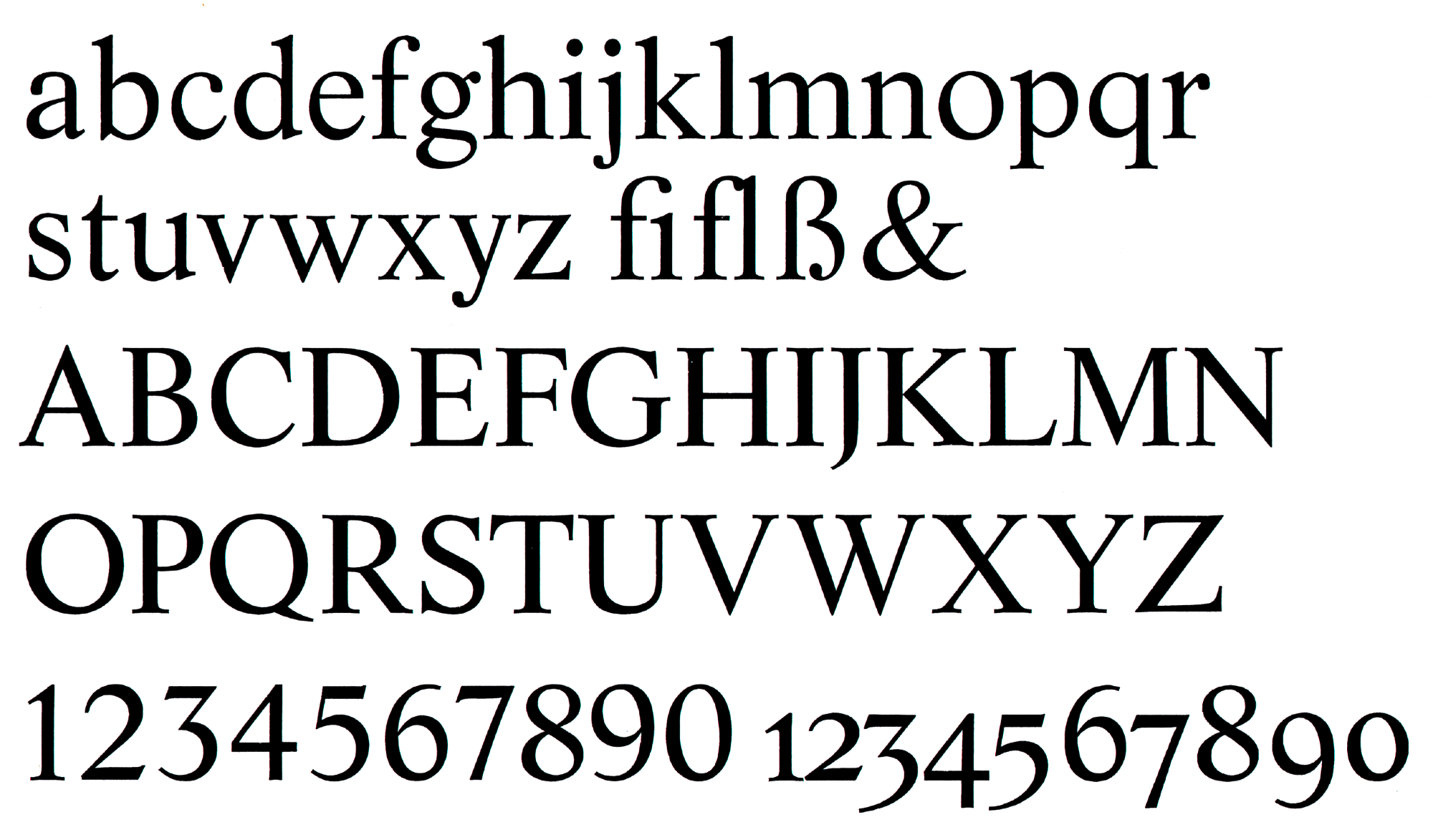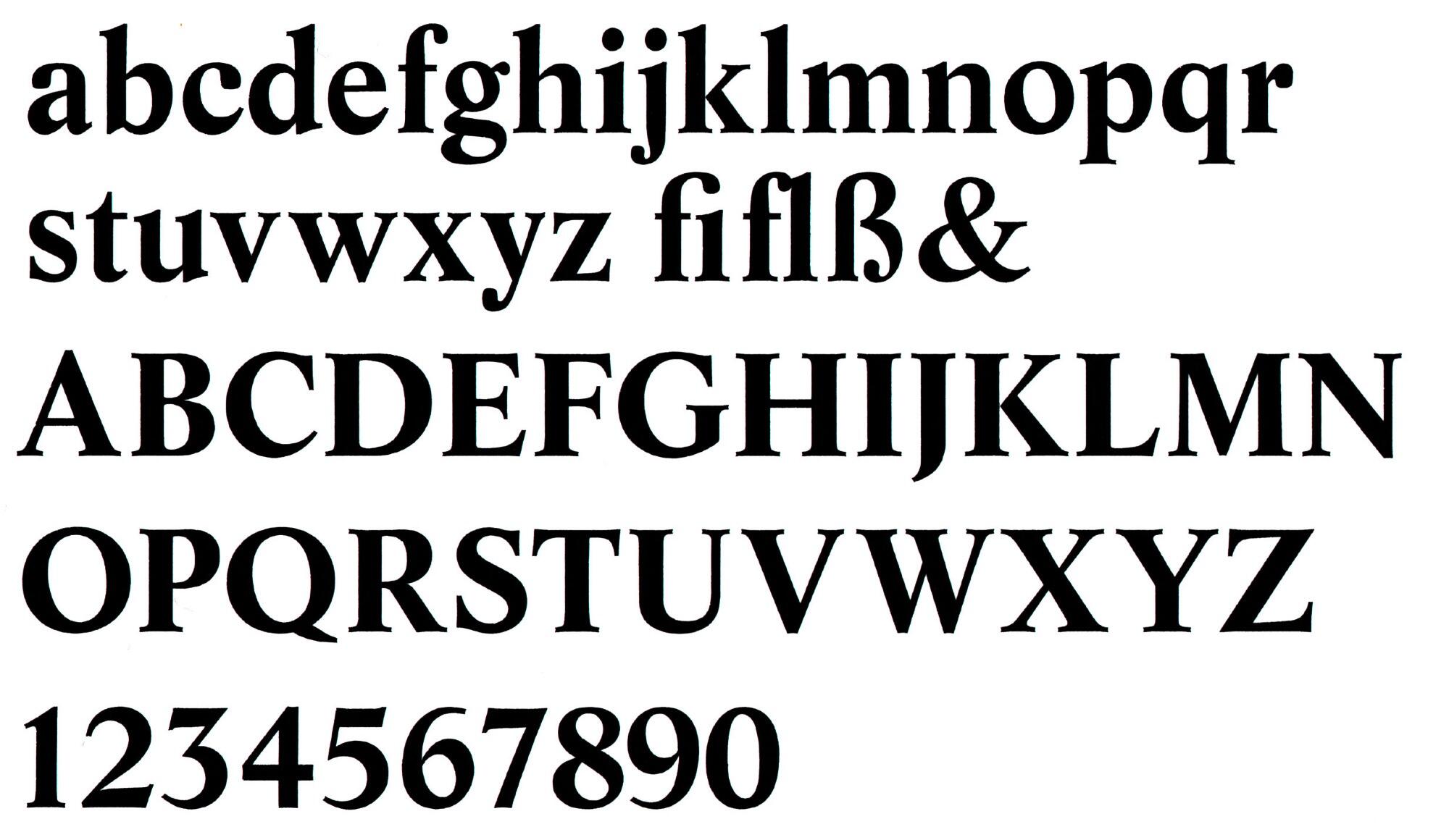
Font-Wiki: Life
Die Life ist eine Zusammenarbeit zwischen dem Setzmaschinen-Schrifthersteller Simoncini in Italien und Ludwig & Mayer in Deutschland. Die eher unspektakuläre Barock-Antiqua erschien in mager, kursiv und fett in den 1960er-Jahren und wurde auch in den Foto- und Digitalsatz übernommen. Heute sind Versionen von zum Beispiel Bitstream, Linotype und URW erhältlich.